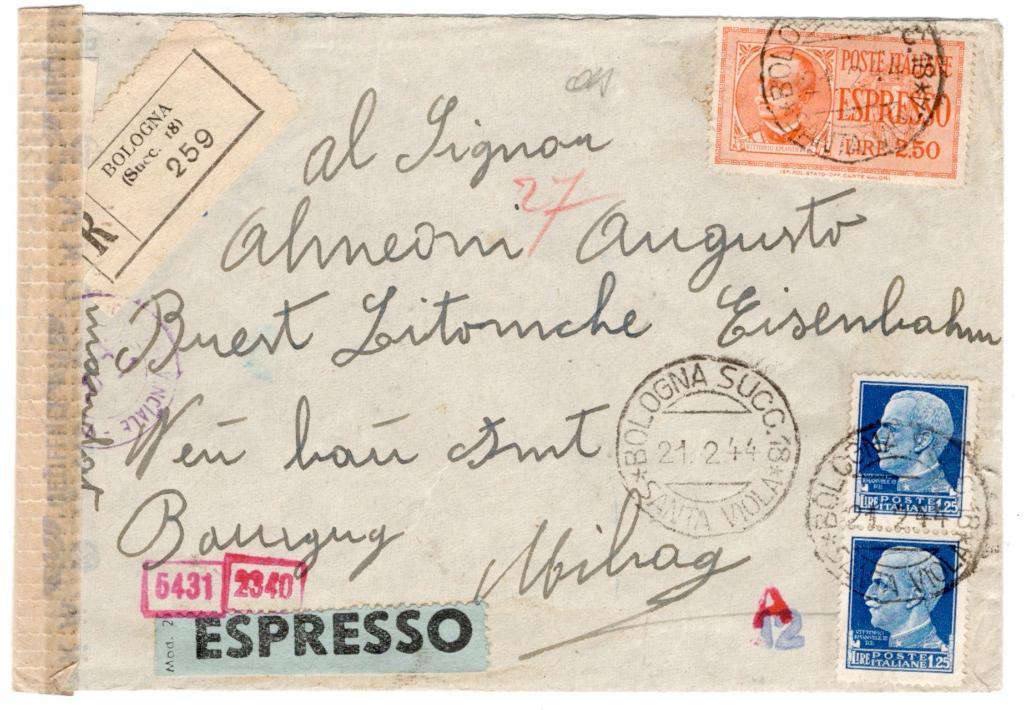
Schrift entziffern
Ich wollte wieder mal  fragen, ob jemand diese Schrift entziffern kann.
Was es schwierig macht, so erscheint es zumindest mir, ist, dass da jemand aus Italien eine Art phonetisches Deutsch geschrieben hat. »Buest Litouiche Eisenbahn« könnte immerhin die »West-Litauische Eisenbahn« gewesen sein … Wahrscheinlich hilft es, da mehr zum Kontext zu wissen.
Der Brief wurde  gestempelt (rückseite)durch die
"Deutsche Dienstpost Brest-Litowsk" stelle.
Ah, dann ist es d0ch ein »r«, kein »u«. Ich hätte drauf kommen können, das r inn Signor sieht ja auchso aus. Und so macht das natürlich auch mehr Sinn.
Dann würde ich »Augusto Almeoni« als Adressaten lesen. Der Rest ist echt knifflig. Käme das hin?
Der Rest ist echt knifflig.
Tja ,das ist auch mein eigentliches Problem.Was danach kommt. :))
Und die letzte Zeile vielleicht:
Bauzug Milag [d.i. Deutsche Treibstoffwerke AG MILAG??]
»Bauzug« würde zu »Eisenbahn« passen, auch wenn der Kringel über’m »u« fehlt. Die Firma taucht auf Listen zum Thema Zwangsarbeit im II. Weltkrieg auf; ob sie dort wirklich tätig war, keine Ahnung.
Sehr plausibel, hatte auch Milag vermutet, war aber davon abgekommen weil via Google keine Ortschaft des Namens gefunden wurde, die irgendwie wahrscheinlich schien.